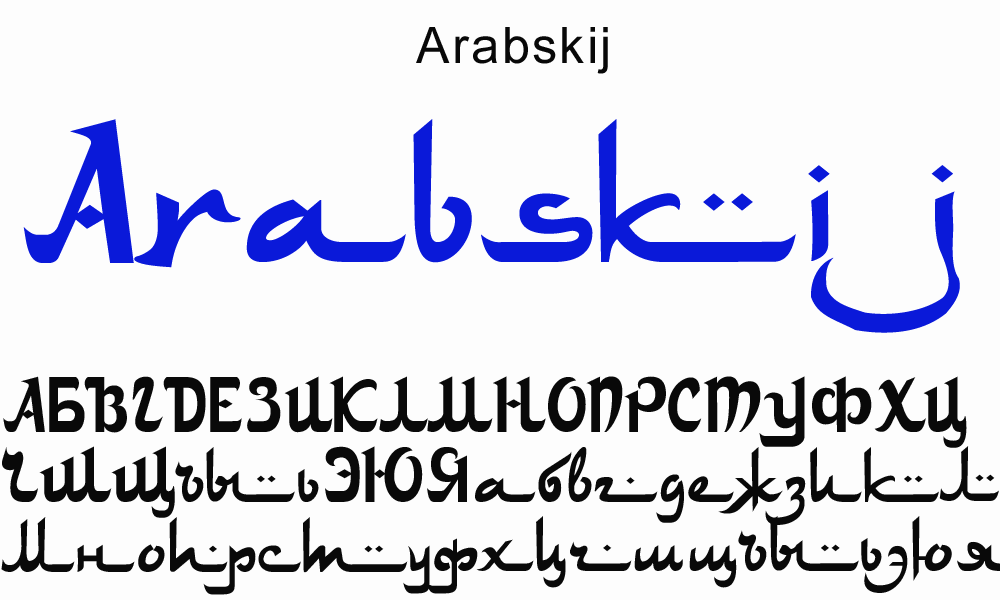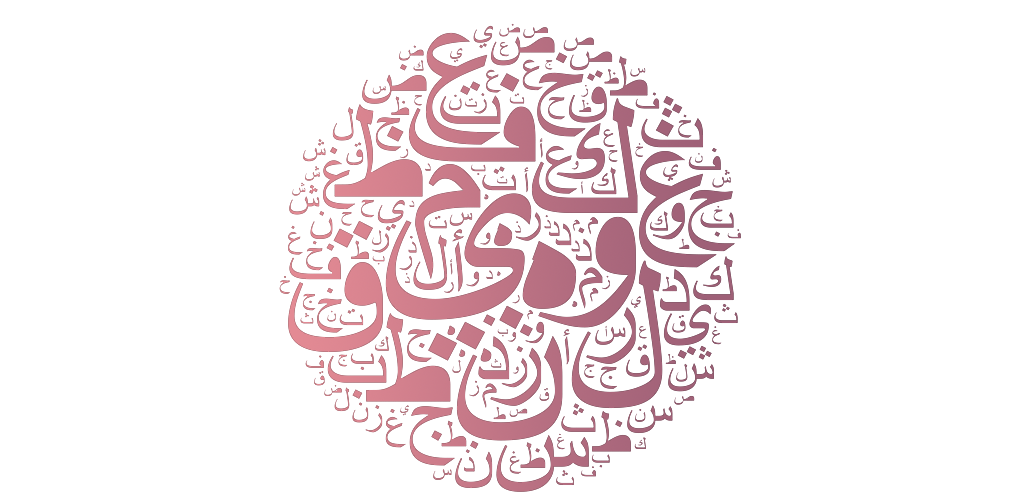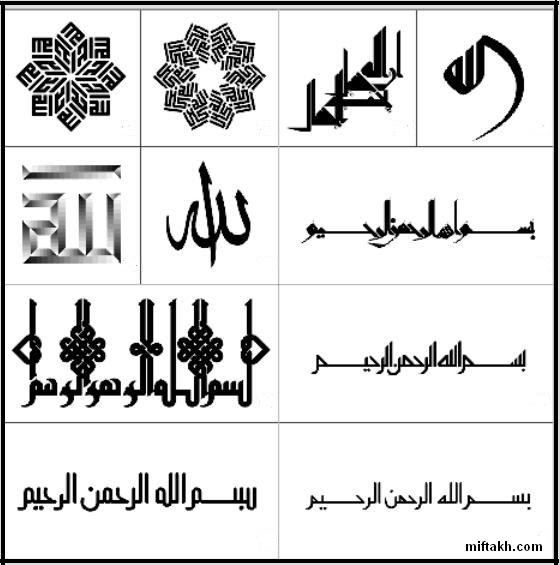
Песок, верблюды, магия, искусство, роскошь, кус-кус и тюрбан — лишь только малая часть образов, которые приходят на ум, когда мы начинаем размышлять об арабском мире. Чаще всего арабский мир характеризуется нами только территорией Ближнего Востока, хотя это лишь часть географической области расположенной на юго-западе Азии. Арабский мир гораздо больше и обширнее. Его география объединяет, в общей сложности, 26 стран с общей численностью населения более 320 миллионов человек, говорящих на арабском языке. Границы этого мира простираются от западного побережья Северной Африки (Мавритания, Западная Сахара, Марокко, Алжир и т.д.) через Катар и Оман до Объединенных Арабских Эмиратов на Ближнем Востоке.
История этого региона настолько глубока и насыщена, что просто не могла не повлиять на искусство, стиль и соответственно на современный дизайн. Чего только стоят арабские шрифты, стиль письма и вся каллиграфия в целом.
Так же очень знаменит особый вид орнамента, называемый арабеской. Он состоит из геометрических элементов или сложных/переплетенных растительных форм (листья, цветы, стебли), а так же включает изысканную графику. Этот стиль можно найти при просмотре сайтов или рекламных плакатов, не говоря уже его большую популярность в архитектуре.
В этой статье мы познакомим вас с дизайном арабских сайтов, а так же покажем красивые примеры написания отдельных букв арабского алфавита и их сочетания в красивых шрифтах.
Дизайн арабских сайтов
Большинство арабских сайтов используют в качестве основного языка английский, либо имеют англоязычную версию.
Очень популярно использование flash-технологий. Несмотря на это есть и форумы, и блоги, и крупные новостные сайты, но, признаться, дизайном они не особо блещут. К тому же из-за специфики алфавита и шрифтов, страницы таких сайтов, для наших глаз, выглядят очень тяжелыми и перенасыщенными.
Типографика. Арабские надписи и буквы
Здесь можно провести параллель с иероглифами. Отдельные буквы или короткие слова смотрятся очень красиво, а в сочетании с уместным использованием правил типографики способны украсить любой сайт или рекламный плакат.
Все символы имеют менее чем отличную форму, что обеспечивает естественный вид в дизайне. Он легко сотрудничает вместе и лучше всего подходит для разработки логотипов в традиционном стиле, этикеток, дизайна упаковки, надписей на футболках и многого другого.
Современный арабский шрифт — один из тех современных шрифтов, в которых нет кривых и выступов при выходе из буквы, вместо этого он угловат и разработан, в первую очередь, на основе геометрической бюрократии и особенностей.